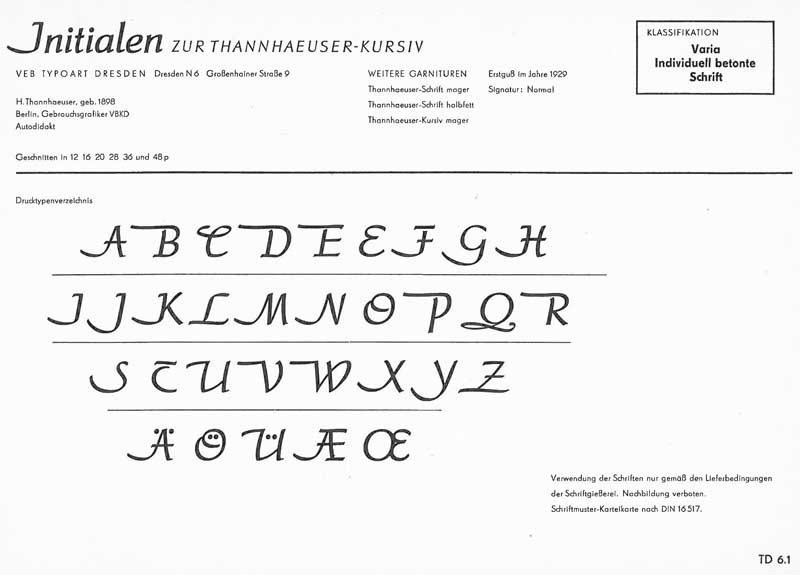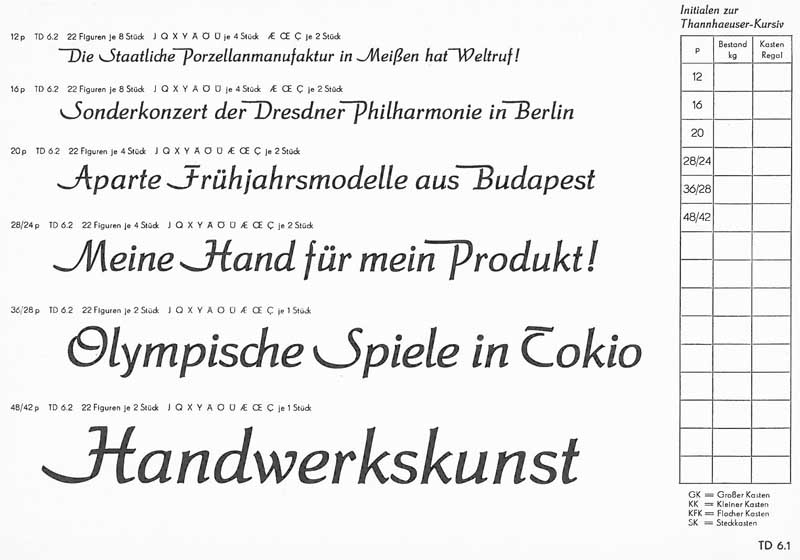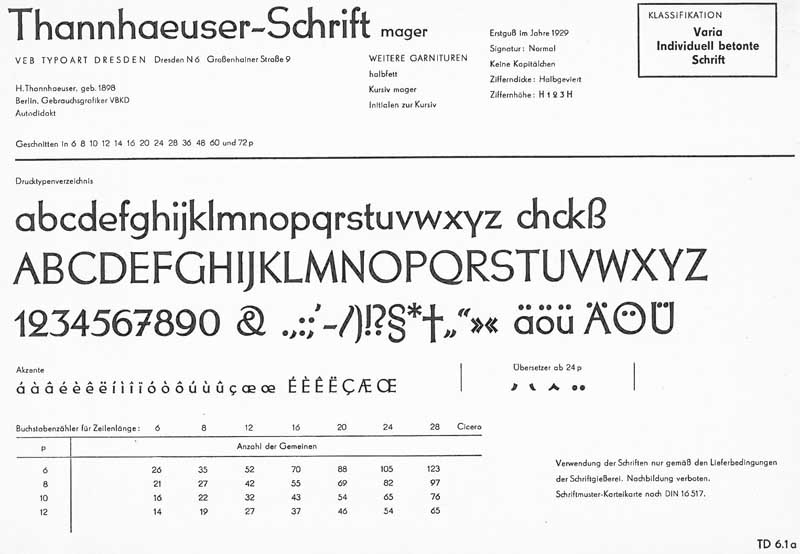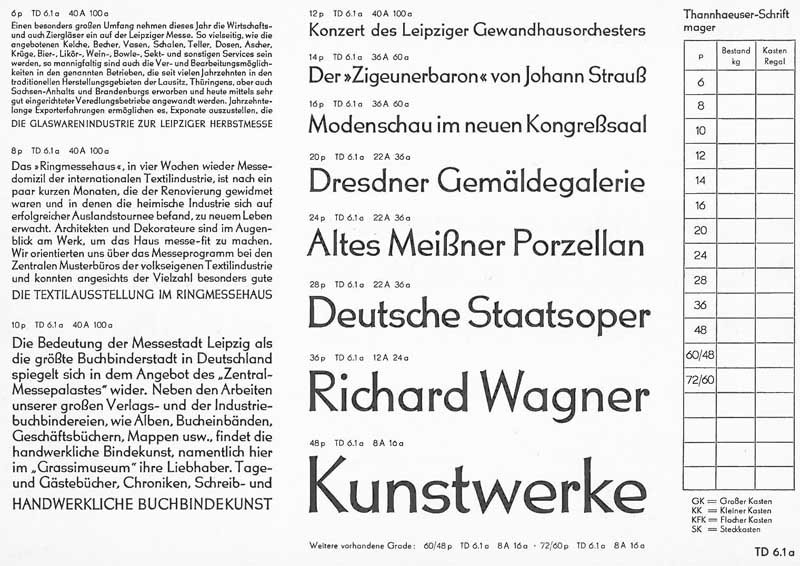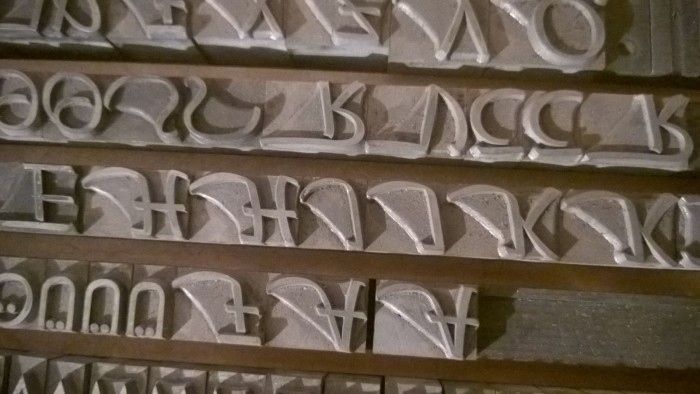
Tannhäuser fremde Versalien?
ich habe kürzlich ein paar Schubladen einer Schrift erstanden, du mit TANNHÄUSER beschriftet sind. Zu allen Schriftgraden finde ich in jeder Lade zusätzlich Versalien einer ganz anderen Schrift, die für mein Auge auch gar nicht dazu passend sind.
Gehören diese Versalien zur Tannhäuser? Kann sich jemand diese Anordnung erklären? Wie heisst die Schrift dieser Versalien?
Anbei ein Foto. Unten links sehr Ihr das "Ü" der Tannhäuser, auf dem Rest die Versalien.
Ö und Ü sind ja entzückend, das sind regelrechte Illustrationen! Die ersten Smileys in der Typografie!  :biglove:
Ja, das war sinngemäß auch mein erster Gedanke. Hier mal noch die Rückseite:
Der Große Wurf sind die Initiale meines Erachtens ja nicht. Aber die Thannhäuser an sich hatte schon was Originelles, auch wenn sie heute ziemlich aus der Zeit gefallen wirkt und ich mir kaum eine aktuelle Anwendung vorstellen könnte. Hier guckt das Ö übrigens etwas erstaunt:
Ja, die Initialen scheinen wirklich etwas außer Rand und Band geraten! Und das normale Ö könnte Bauchgrimmen haben …